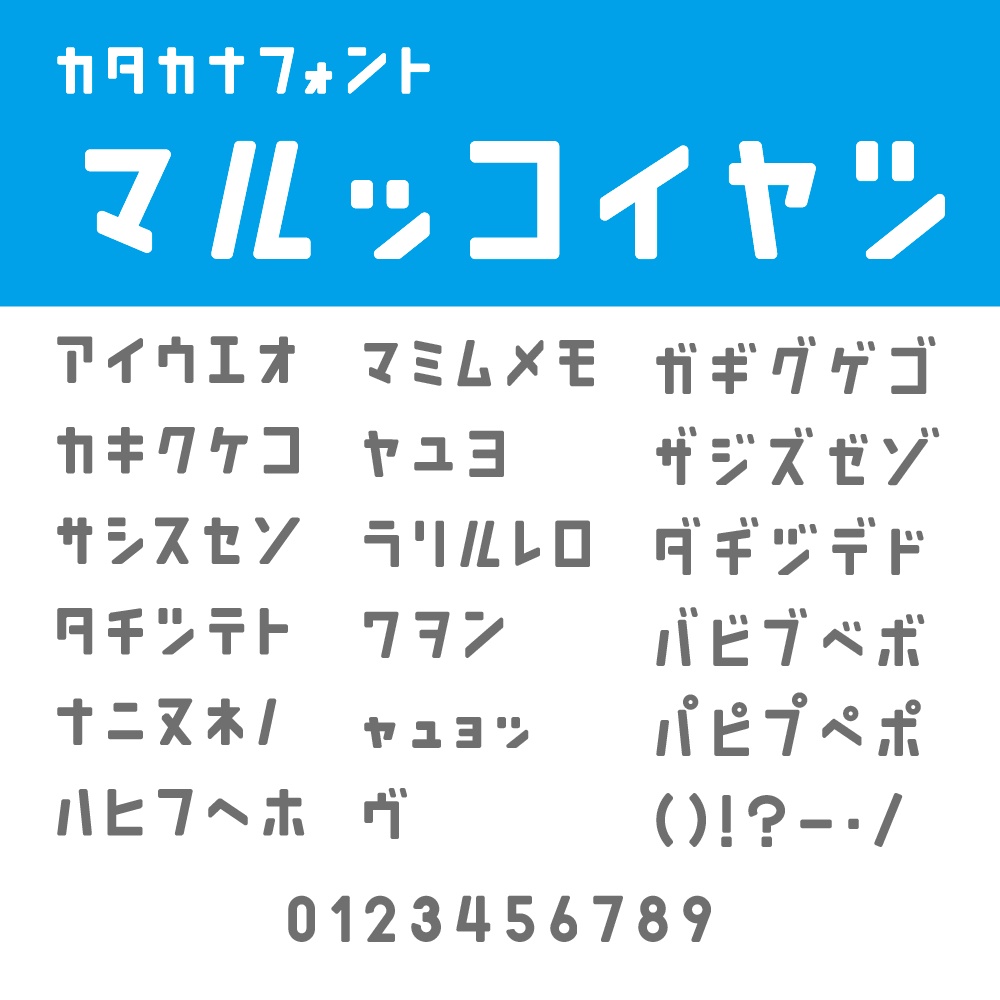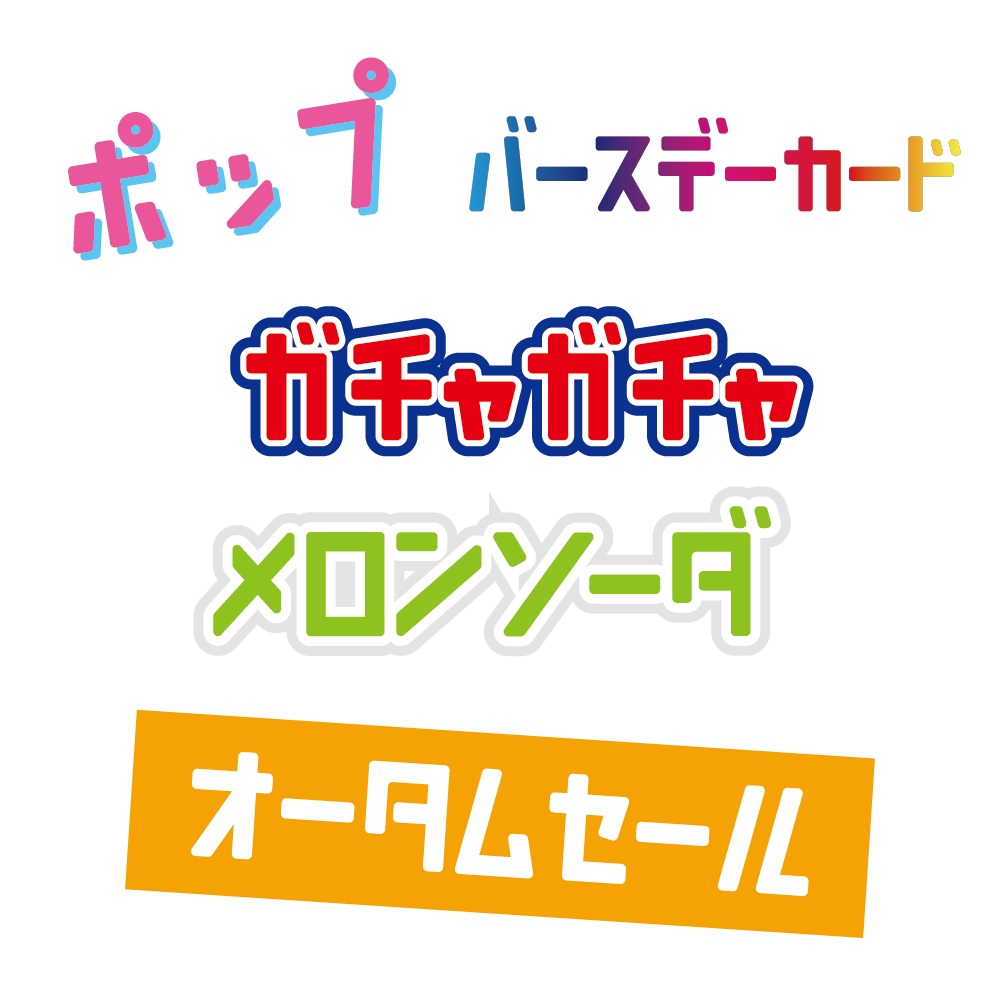
マルッコイヤツ(カタカナ専用フォント)
【概要】 角の取れたコロンとしたシルエットが特徴の、カタカナ専用の丸ゴシック風フォントです。 直線となめらかな曲線を組み合わせることで、親しみやすくポップな印象を与えます。 カジュアルなタイトルやかわいい世界観のデザインにフィットしつつ、シンプルなレイアウトにも合わせやすいバランスを意識して設計しています。 【収録文字】 ・全角カタカナ ・欧文数字 0〜9 ・一部記号(ー()!?・ など、基本的な記号のみ) 【想定用途】 ・ポップ・カジュアル系のタイトルやロゴデザイン ・キャラクターグッズや雑貨などのパッケージデザイン ・YouTube サムネイルや SNS 用画像のテキスト ・ポップで可愛い雰囲気の Web サイト見出し ・イベントフライヤーやショップカード など 【対応環境】 ・フォント形式:OpenType フォント(.otf) ・動作確認済み:Windows 10 / Windows 11(日本語版) ・上記以外の OS(macOS など)や一部アプリケーションでもご利用いただける場合がありますが、 作者は動作保証・サポートを行っておりません。 【カーニングについて】 ・カタカナ向けのカーニング情報を含んでいます。 ・Adobe Illustrator / InDesign などの DTP ソフトでは、文字パネルの「カーニング」を「メトリクス」に設定してお使いください。 ・Web フォントとして利用することも可能ですが、カーニングの反映状況はブラウザや環境に依存します。 環境によってはカーニングが反映されない場合があります。 【ライセンス/利用範囲(有料版)】 ・個人・商用利用どちらも可能です。 ・本フォントを使用して作成したロゴ、画像、動画、印刷物などの成果物は、自由に配布・販売していただけます。 ・ただし、本フォントを使用して作成したロゴ・マーク等を商標登録・意匠登録することはできません。 ・フォントファイル自体の再配布・再販売、フォントデータを改変して別フォントとして再配布する行為は禁止です。 ・1 ライセンスにつき、ユーザーが所有または管理する 2 台までの PC でご利用いただけます(同時使用は同一ユーザーに限ります)。 ・詳しい条件は同梱の「EULA.txt」を必ずご確認ください。 【ファイル内容】 ・フォント本体(.otf) ・EULA.txt(利用規約) ・README.txt(概要と注意事項) 【注意事項】 ・本フォントおよび本フォントを用いて生成した画像・アウトラインデータを、機械学習・AI モデルの学習データとして使用することを禁止します。 ・フォントの表示結果やカーニングは、OS やアプリケーション、ブラウザ、描画エンジンの違いにより異なる場合があります。 必要に応じて文字間や行間を調整してご利用ください。